Update: Der singapurische Fußballshop WestonSG hat ein großartiges Bild der Nike Südkorea 2020 Trikot-Schriftart geteilt.
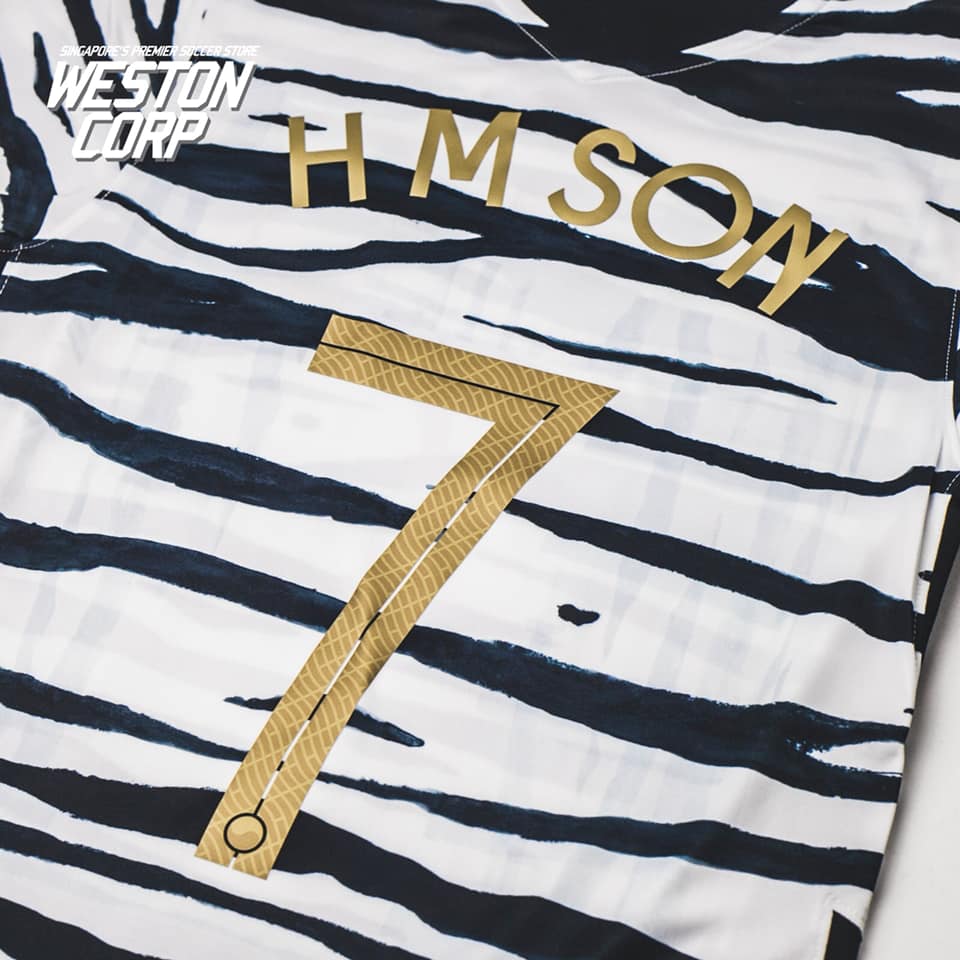
Nike hat die Schriftart für die Südkorea 2020 Trikots veröffentlicht. Es ist noch nicht bekannt, ob die Schriftart exklusiv für die südkoreanische Fußballnationalmannschaft entworfen wurde.
Die Schriftart des Nike Südkorea 2020 Trikots besticht durch einen modernen und geschmeidigen Look. Die Schriftart hat viereckige Looks für die meisten Nummern, abgesehen von der Nummer 7.
Die Schriftart des Nike Südkorea 2020 Heimtrikots ist schwarz mit dem rot-blauen Taegeuk der Flagge am unteren Ende, während die Schriftart für das Auswärtstrikot golden ist, wobei Taegeuk nur angedeutet ist.
Die Schriftart für das Nike Südkorea 2020 Trikot ist bisher nur in Südkorea verfügbar.
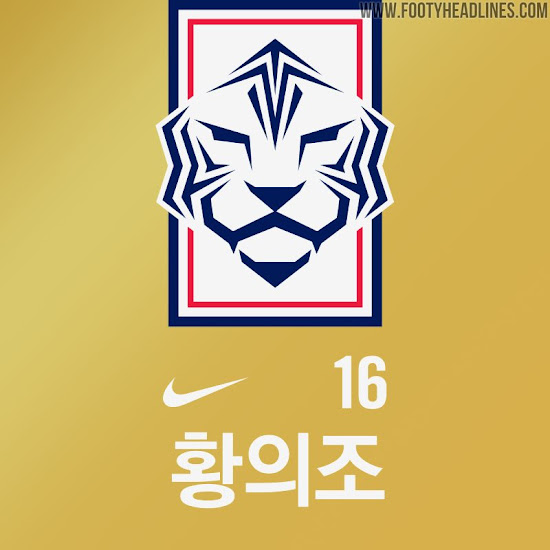
Nike Südkorea 2020 Trikot-Schriftart